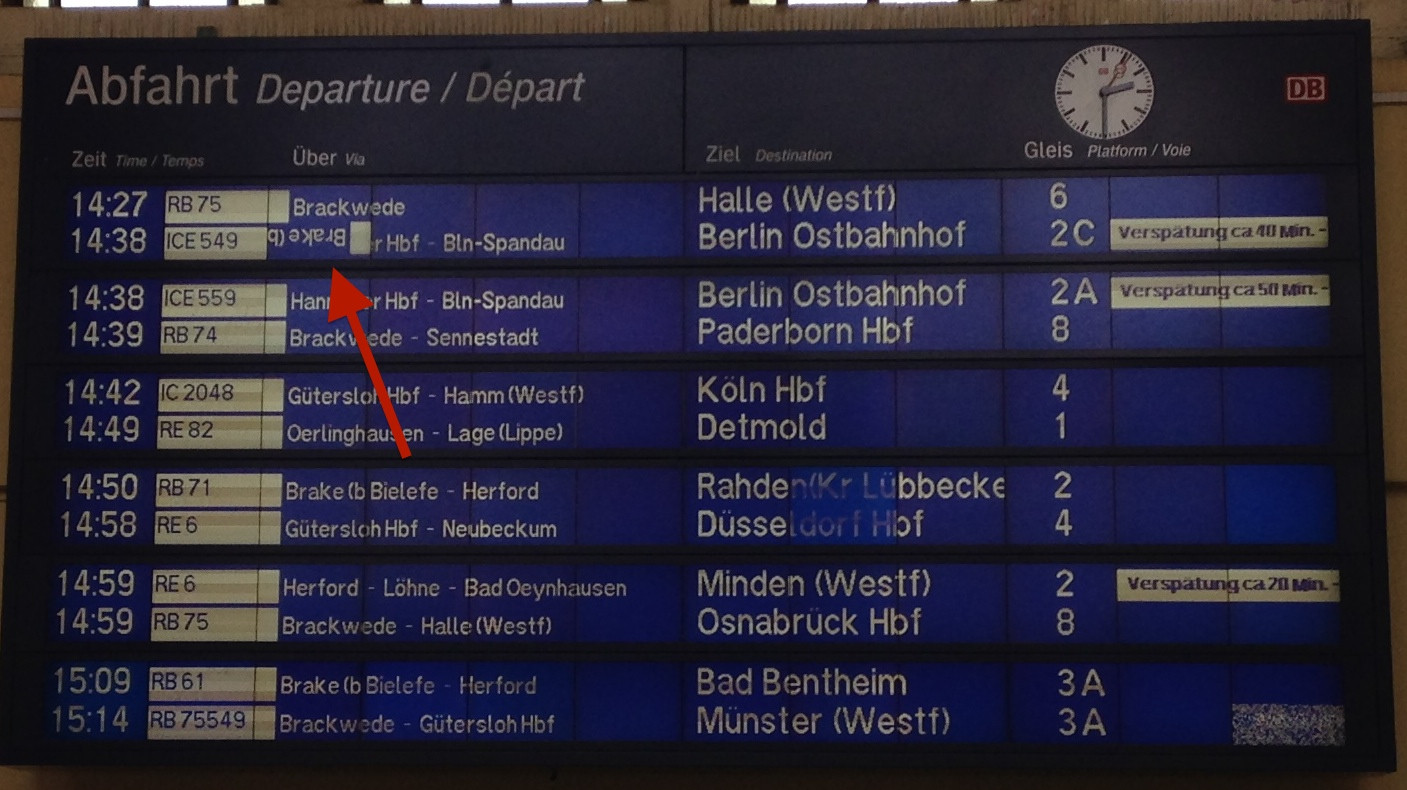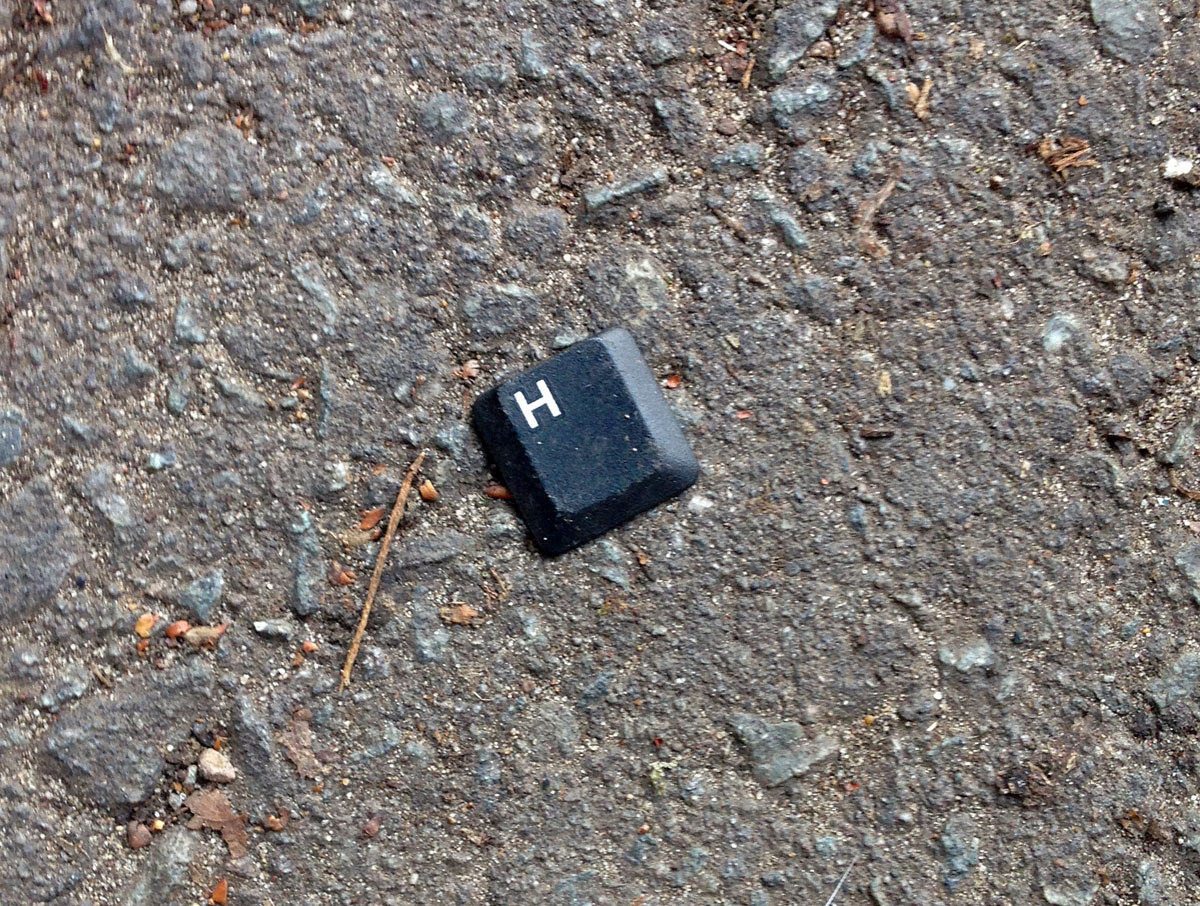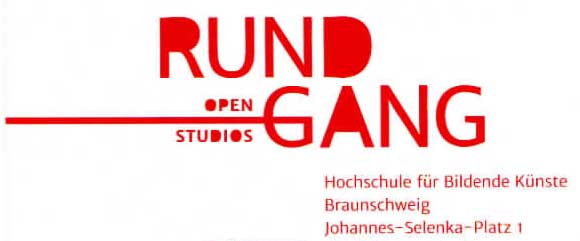
Dieses im wahrsten Sinne des Wortes typografische Fundstück lag mir heute auf dem Heimweg plötzlich zu Füßen :bow:  :-)
Sc_ade ist nur, dass jetzt wo_l irgend so ein armer  _und o_ne  _  auskommen muss …  :shock:  :cry:
AC|-|, ALLES NUR |-|ALB SO SC|-|LIMM! ;)
Hier ein Fundstück aus dem sagenumwobenen Bielefeld, das ich nach bestandener Eignungsprüfung :party: für den Gestalter-Studiengan an der FH entdeckt hab …
Ich frage mich, was da schief gelaufen ist, denn offensichtlich ist nur ein halber Bildschirm betroffen …
Wenn sich dann diese G-Verlängerung als roter Faden dann durch alle zum Rundgang gehörenden Räumlichkeiten zieht. also z.B. ein paar Rollen rotes Tüten-Zuklebe-Klebeband von diesem Ponkt aus überall an der Wand entlang geklebt sind. Das mit den vollgelaufenen Punzen ist aber wirklich doof, zumal, recht inkonsequent, dann hätte es bei diesem ersten G auch so sein müssen.
Dann hätte ich das G aber nicht durchgestrichen, sondern nur die Höhe und Stärke des G-Strichs aufgenommen und eine deutliche Lücke gelassen.
Geb ich dir recht. So ist es jedenfalls nicht einer "Hochschule für bildende Kunst", sondern höchstens einer "Schule für eingebildete Kunst" würdig.
Ich frage mich, was da schief gelaufen ist, denn offensichtlich ist nur ein halber Bildschirm betroffen …
bei uns gibts auch eigenartige erscheinungen auf der anzeigetafel: